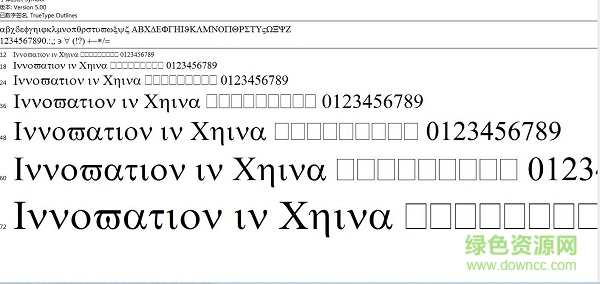
symbolmt.ttf字體是一款用途十分廣泛的普通符號(hào)字體,該字體包含了各種數(shù)學(xué)公式,如果你的電腦符號(hào)出現(xiàn)亂碼,可以下載該字體進(jìn)行安裝修復(fù),有需要者歡迎體驗(yàn)!
Symbol字體用于數(shù)學(xué)公式中,包括希臘字母、數(shù)字、運(yùn)算符、集合符號(hào)和其它符號(hào),可以解決你office里面數(shù)學(xué)公式亂碼問題。